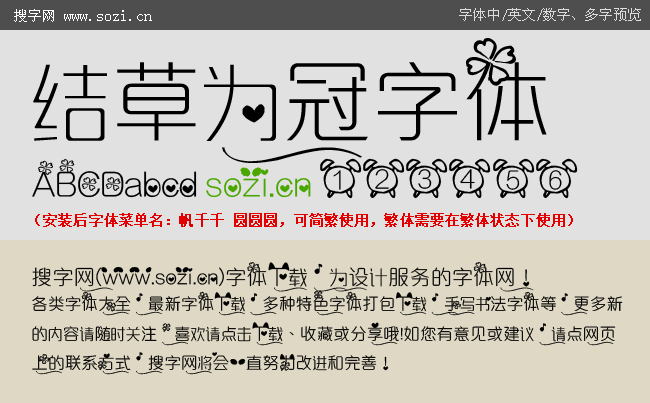
結(jié)草為冠字體
搜字網(wǎng)給大家提供一款結(jié)草為冠字體手機(jī)中文字體下載。這款手機(jī)字體是將悅圓體字體為原形,字體間嵌入可愛(ài)的卡通圖案。造字工房悅圓常規(guī)字體為圓體字形,結(jié)構(gòu)秉承悅黑系列,筆畫風(fēng)格簡(jiǎn)潔,柔美優(yōu)雅。加入卡通圖案后趣味性實(shí)足,又保持了文字的識(shí)別度,特別適合喜歡手機(jī)字體個(gè)性一些的朋友在手機(jī)上安裝使用。